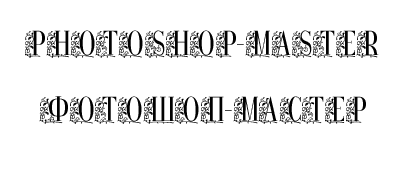
Великолепные шрифты, огромное спасибо!
Честно..Неочень..
Super супер
очень красиво)
одна и таже завитушка на всех буквах...........
Спасибо!Очень понравился!
Вах! Супер!=)))
Класссный!!
Класс..(=
руско - народный
Супер ))))))))))))))
нет слов!!! шикарно!!!
Вааауу...СПАСИБО!!!СУПЕР!!!
Жеесть!!! Шрифт-Супер просто, Спасибо большон=)))
Именно то, что искала. Спасбо большое!!!!!